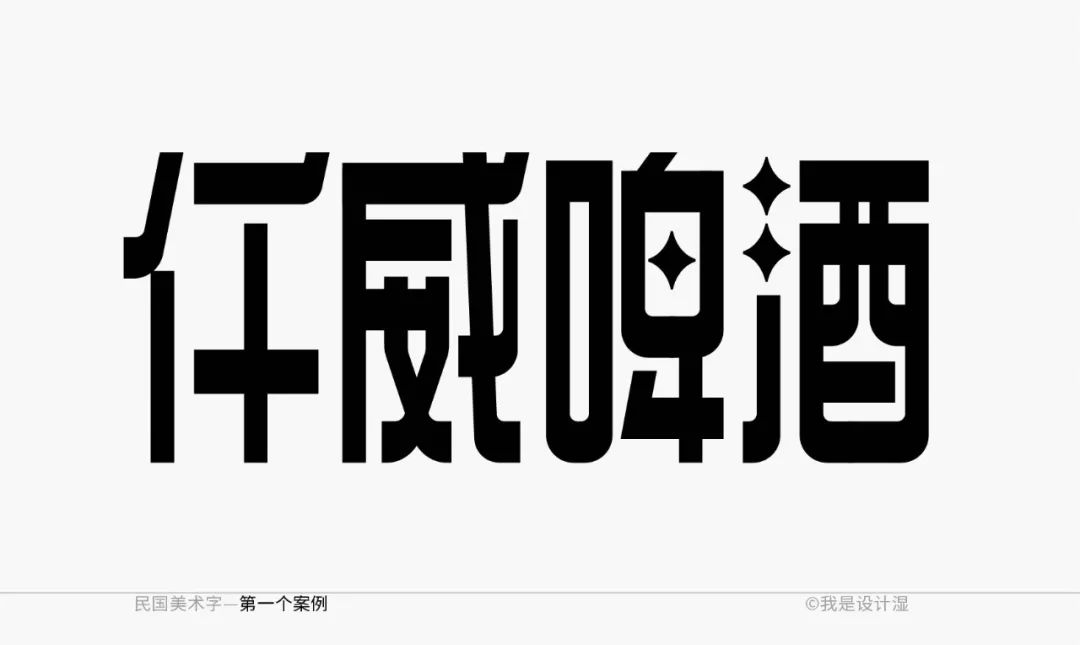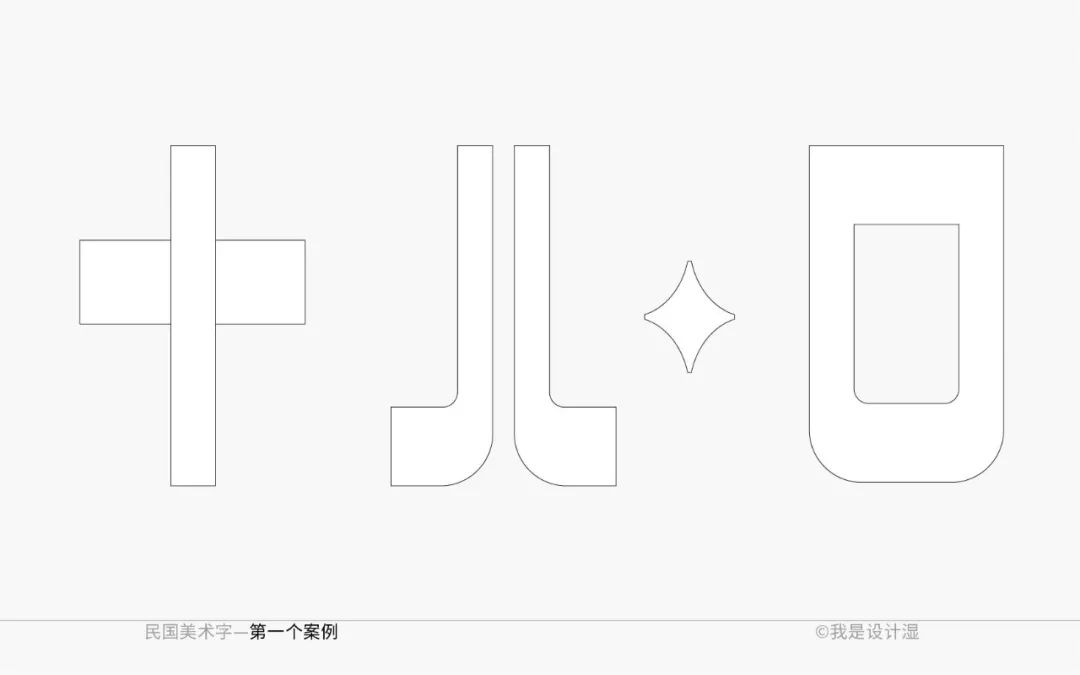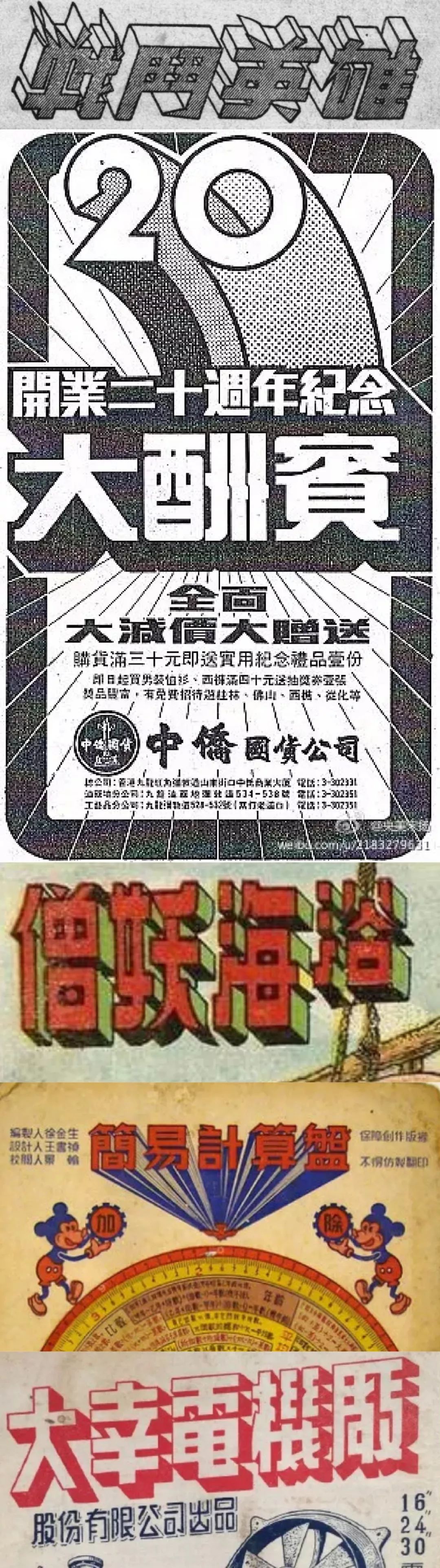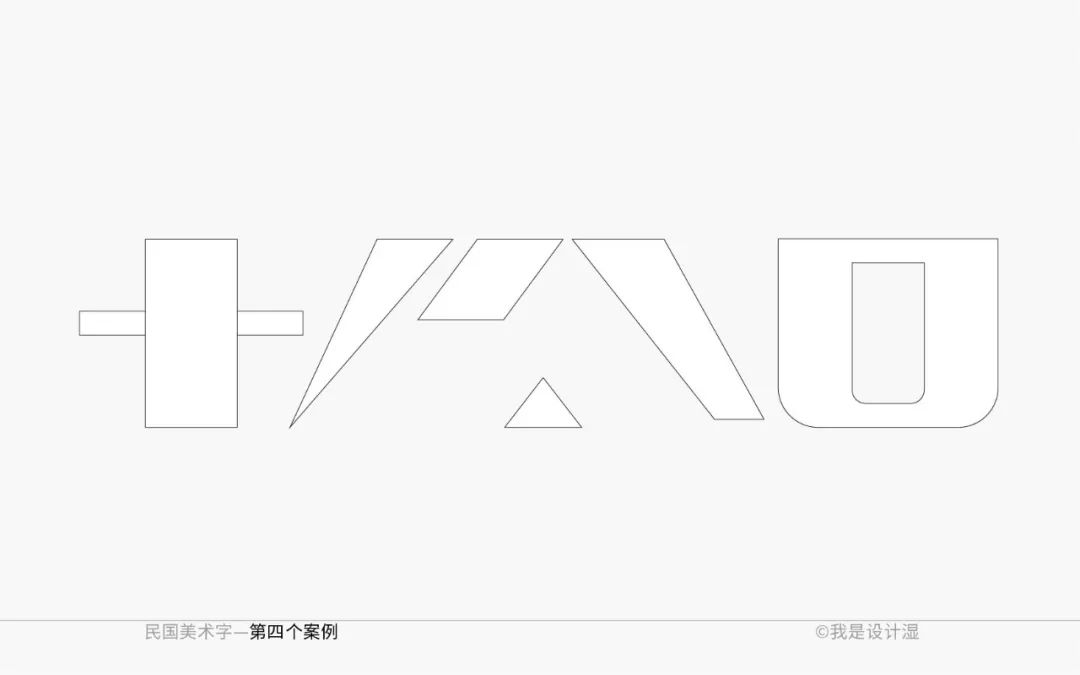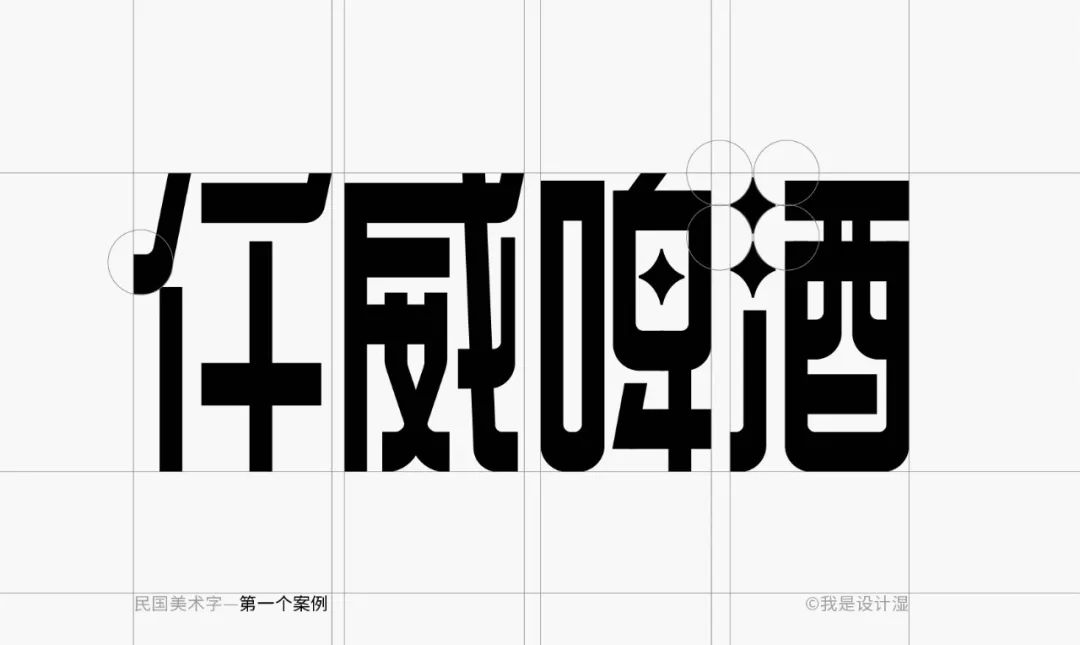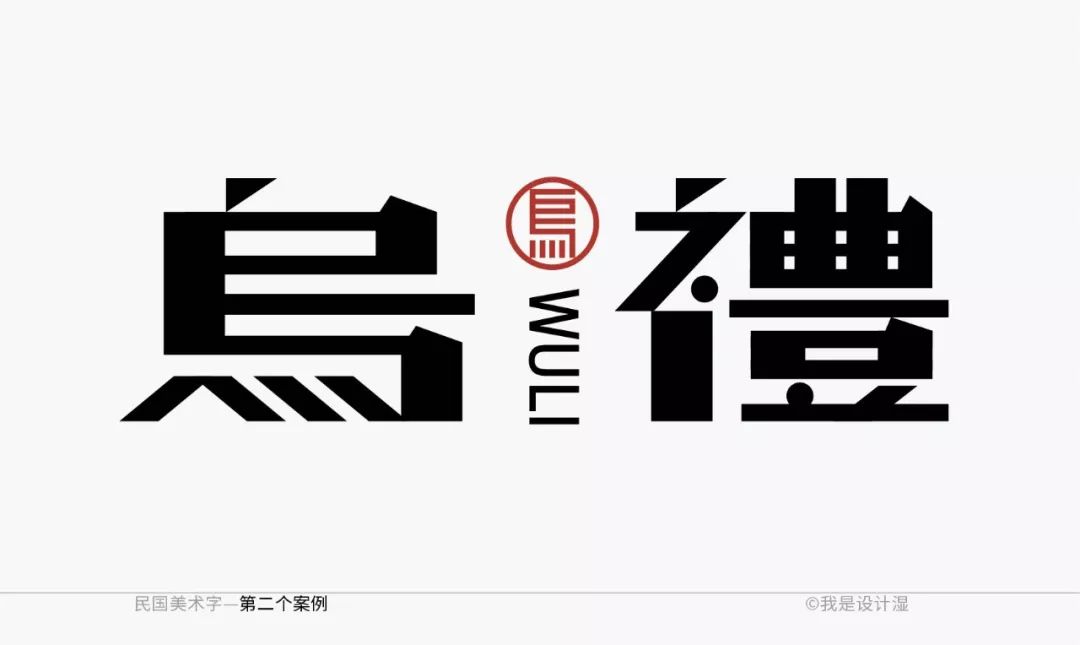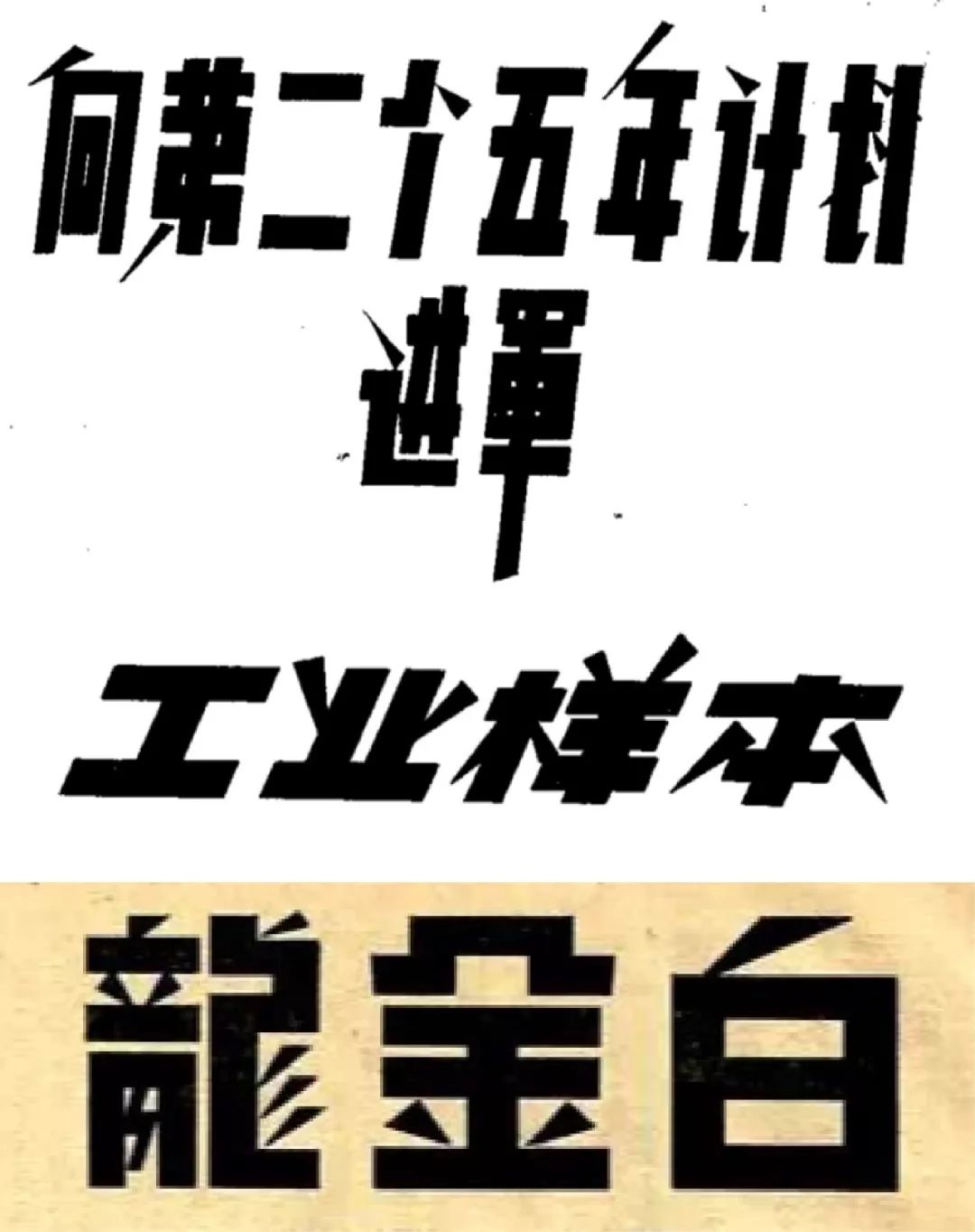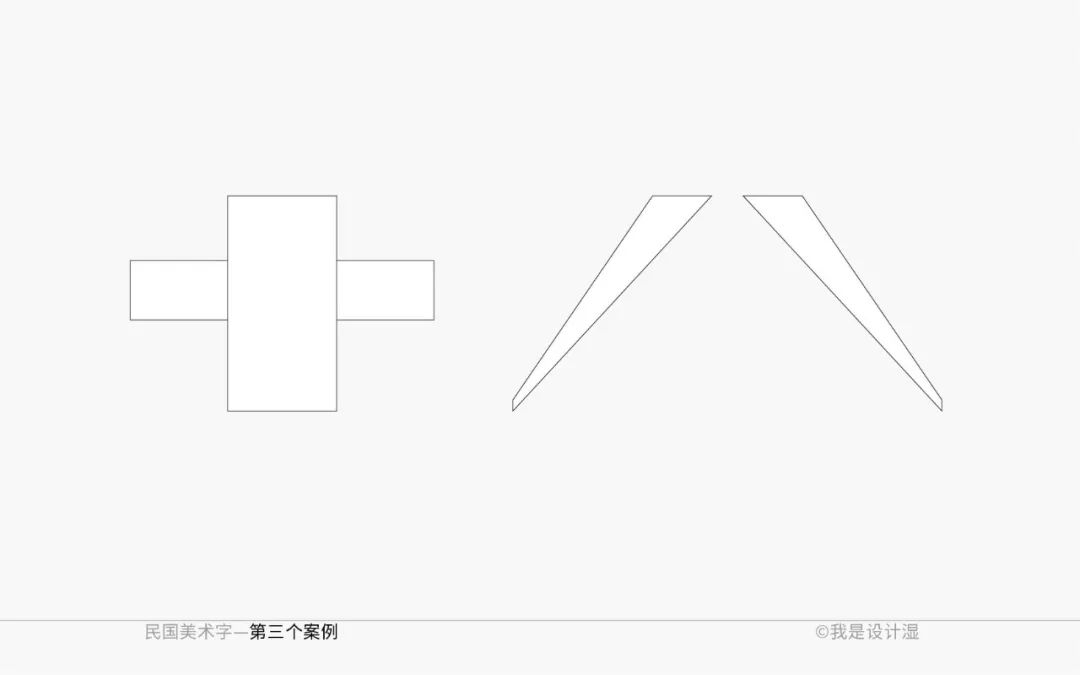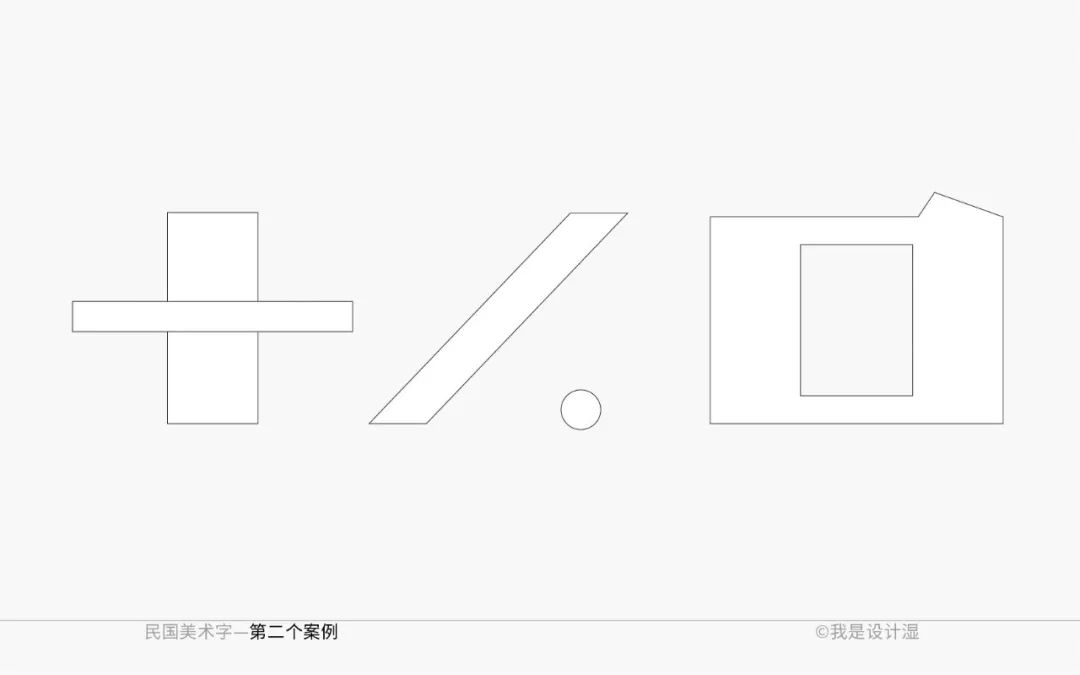
灵感枯竭?教你从民国美术字中找灵感
前段时间集中式的看了许多关于民国美术字的案例,越看越心虚,才发现尽管我们目前已经用电脑开始进行这样的美术字形的设计,有了很多工具上的辅助,对齐裁切效果有非常多看上去很高级的工具了。但是相较七八十年前,至今的字体设计行业好像也没有特别大的发展。
比如立体字,其实现在大部分设计师都是画不出来的,甚至用电脑也做不出来。但是我们看到民国都有许多这样的案例,甚至目前有许多的立体效果字,基本上还是参照那个时期的一种延续和改进。
看到这里许多同学可能陷入了自我怀疑式的沉思。
甚至我们目前电脑上的很多很多字库,灵感都是来自于民国时期一些美术字的启发,但仍然还有许多案例未被“利用”殆尽,所以这一期我们用五个案例来示范一下,如何去借鉴参考,然后完成自己的作品。
美术字的案例是非常多的,首先如果你有比较多的字体设计需求的话,我的建议是,整理成一个比较大的素材库,这当然需要一个收集的过程。
我们来看第一个案例,第一步当然是首先找到你想要的参考方向。
这个字形的特征性非常的强烈。
第一是,横粗竖细,这是我们很难见到的粗细比例。
第二是,撇捺的变化。
第三是,点的特殊处理。
第四是,口的圆角处理。
那么确定好粗细变化及笔画特征之后,我们需要把这些笔画利用到我们要做的题目当中去。
尽管字的特征是非常多比较花俏的,但是还是要把细节的部分处理好,这很重要。
这其中有几个部分的笔画我做到了尽量统一,我们来看一下细节。
我们来看第二个案例,先找参考方向。
这个字形的特征性也非常好,尽管细看的时候我们会觉得它基础笔画的处理不是那么的完全统一,但毕竟是美术字的范畴,整体的特征感受统一即可。
来提取一下笔画,找你觉得突出的部分挑出来。
我们挑出来特征后会发现,特征有一些不够,所以在这个字形当中需要自己再次发挥创造,不能局限于参考。
用标准制图检查细节,如对齐或笔画分布均匀等。
看一下具体的细节呈现,主要从几个特征表现的。
第三个案例,这一组我找到得参考方向还是蛮多的,主要这类字形你可能也经常见到,但是你不一定用过。
毫无疑问,这个字的特征主要来源于干脆利落的撇捺点的变化,甚至其他部分的特征都可以忽略不计。
需要注意的是,撇捺特征不光是来自粗细过渡,而且它整体的粗细是竖笔粗细的一半都不到。
当然了,为了完善一下特征,我还是自己发挥了一些特征添加进去,而且整体呈现的排版节奏也更加灵活。
这里参考线的意义主要是提醒字距应该适应留白面积,而不是完全等大。
看一下具体的细节呈现。
第四个案例,这组字的特征主要来自于三角形的使用,难度系数比较好,不适用所有题目,且需要斟酌细节较多。
那我得题目是“酱小兔”,所以肯定不能做这样硬朗,就算加三角形,我也是打算给它一定的圆角,或者让整体更加圆润一些。
看一下最后效果。
最后的部分我加了一下圆角进去,为了适应这个题目的感觉,不要像原来那样锐利。
看一下具体的细节呈现。
第五个案例,我找了一个曲线一些的感觉,毕竟前面示范的偏硬朗,换个口味。
看参考。
还是先来总结基础笔画,特别是对于一些相对复杂的字而言,基础笔画意味着基础统一,不会出现特别大的错误。
看一下最后效果。我搭配了一个曲线感非常强烈的英文,一方面吻合题目,一方面配合中文。
规范细节,再次说明,这个参考线大部分时候就算不为了展示给客户,也尽量要画一遍,很多不规范的细节未画参考线之前未必能注意到,往往容易忽略。
下面是具体的细节呈现。